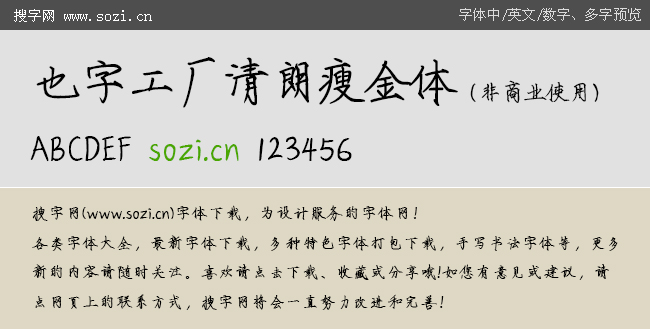
也字工廠清朗瘦金體
搜字網(wǎng)給大家提供一款也字工廠清朗瘦金體(非商業(yè)使用)中文字體下載,也字工廠清朗瘦金體是一款手寫書法字體,其字形俊秀、遒勁有力,優(yōu)雅中透出知性的氣息。文從字順,字形筆畫柔美俊秀、剛?cè)岵?jì),結(jié)構(gòu)自然灑脫,充滿活力朝氣的青春氣息。適合應(yīng)用于書籍畫冊(cè)、海報(bào)、網(wǎng)頁(yè)設(shè)計(jì)等應(yīng)用(此字體為個(gè)人非商用版,商用可以聯(lián)系:官方網(wǎng)址:https://yefont.com/home,聯(lián)系方式:13798980448)。